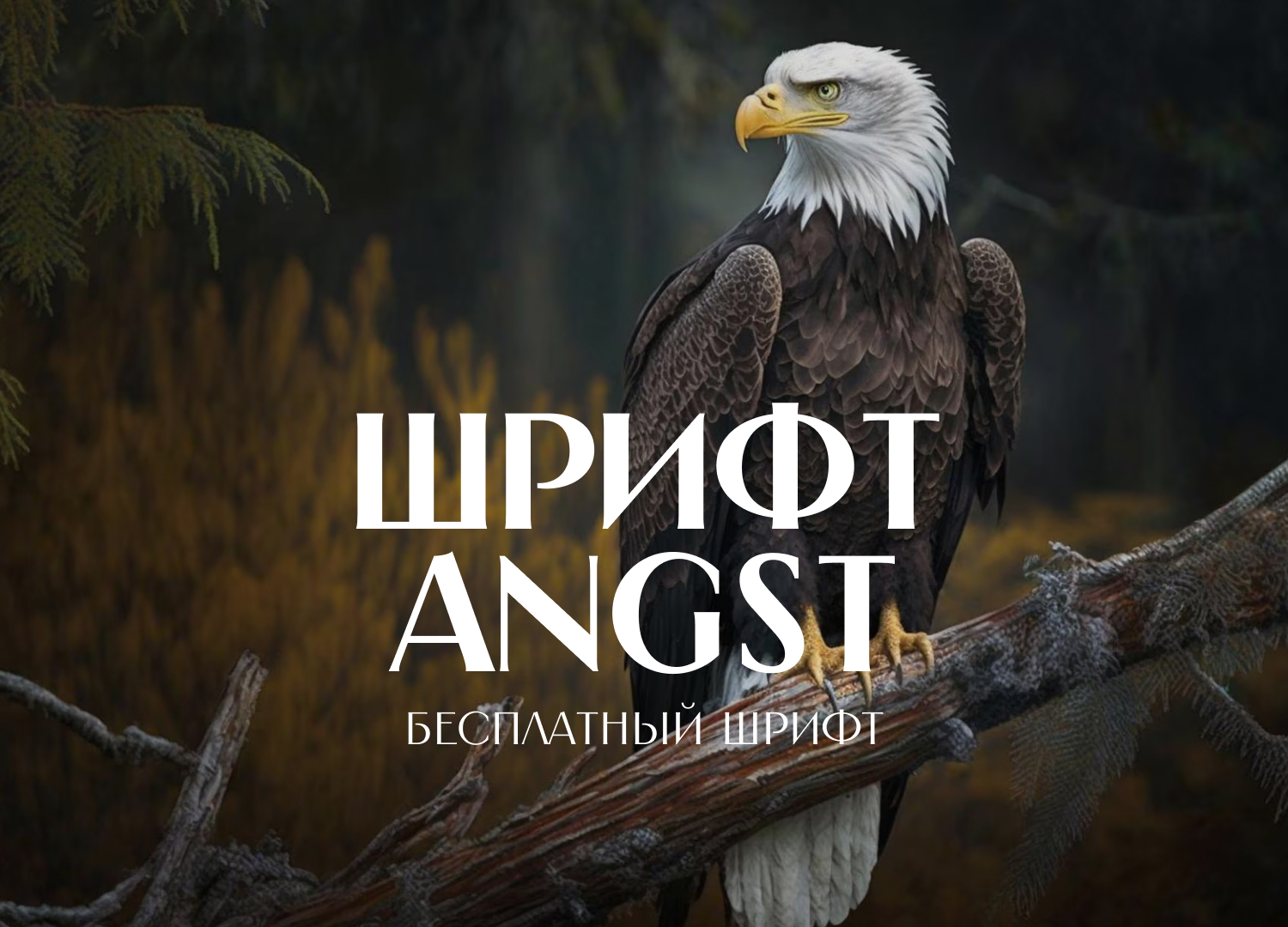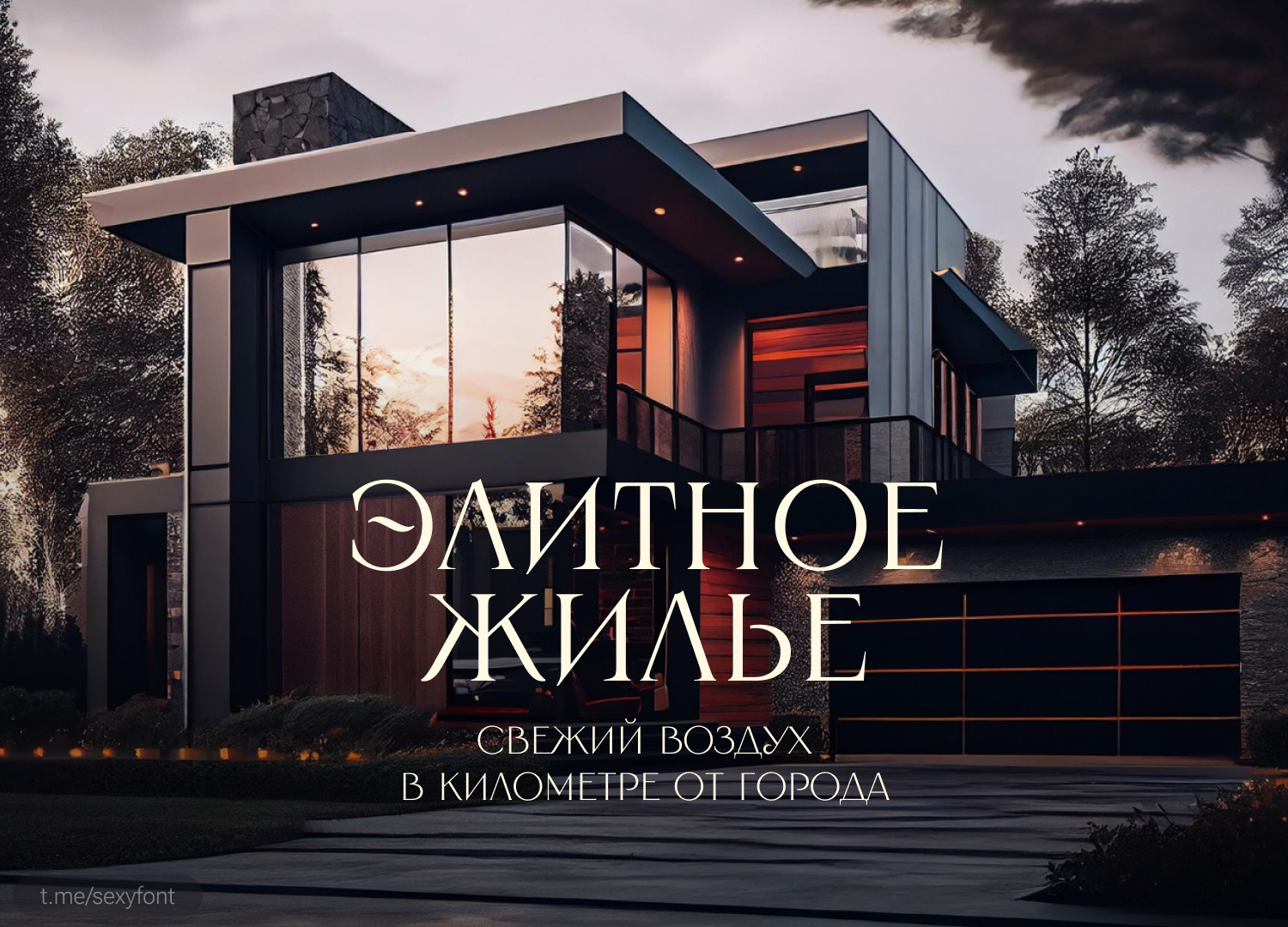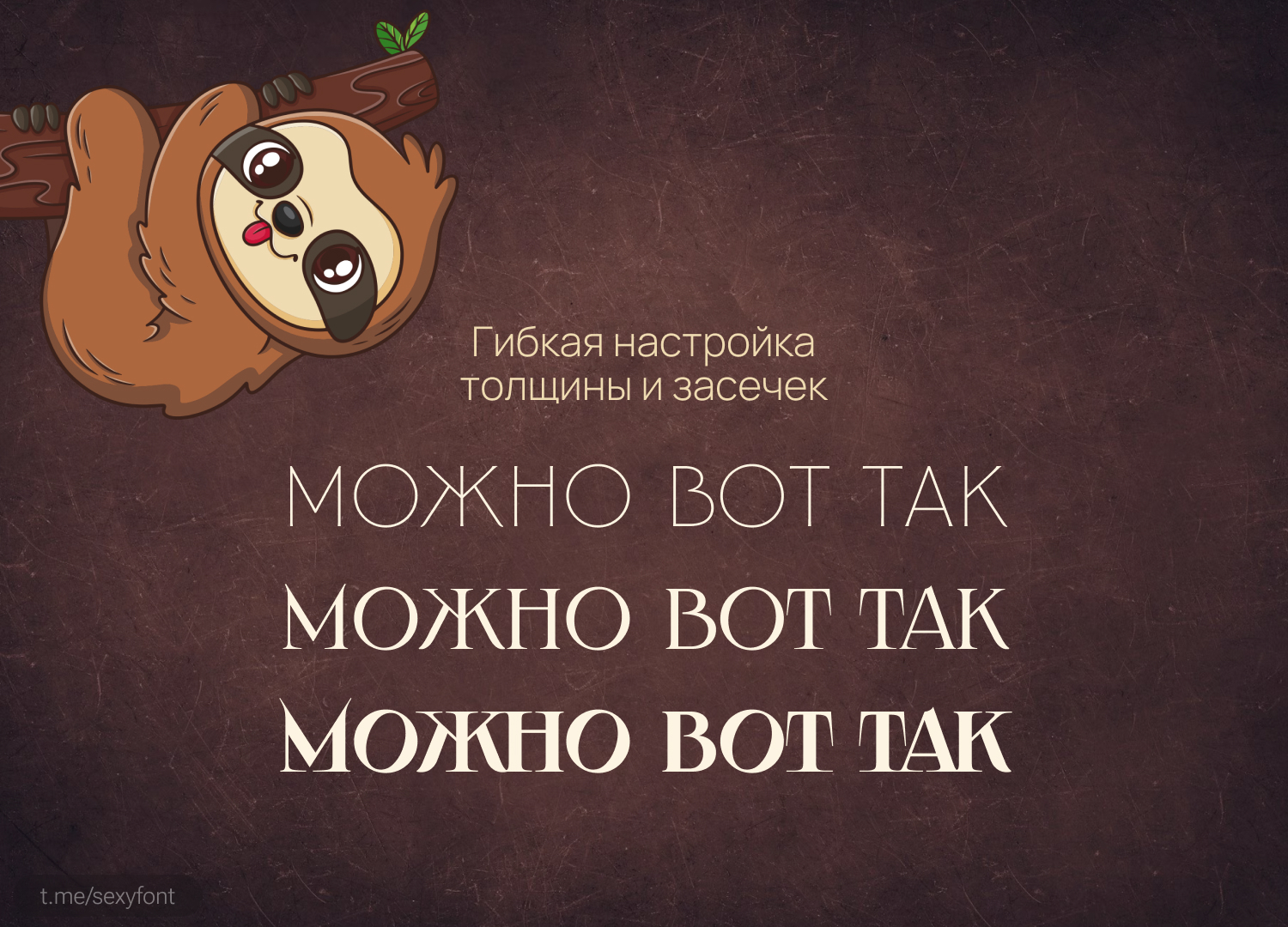
Бесплатный шрифт Angst
Йоу. Новая презентация. Крутой вариативный шрифт с возможность регулировать толщину букв и длину засечек. Показал в презентации разные вариации.